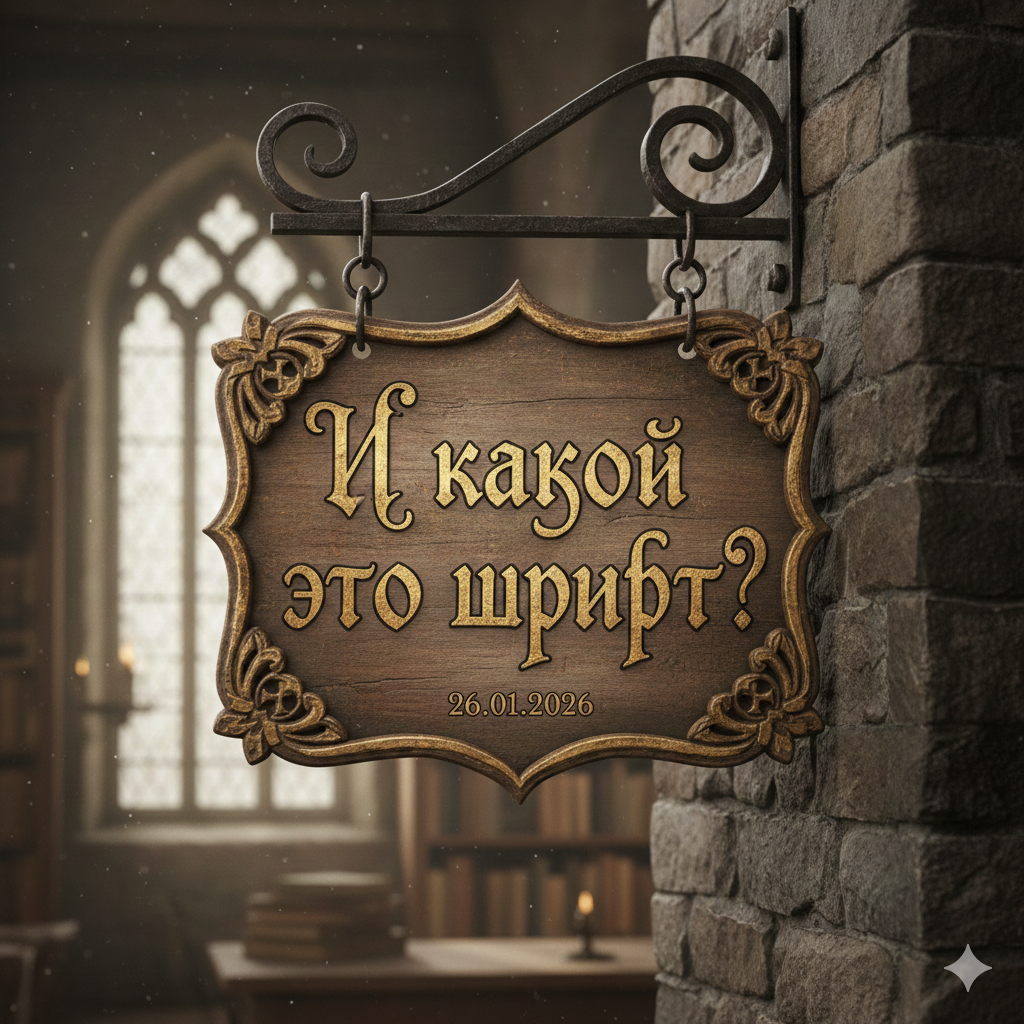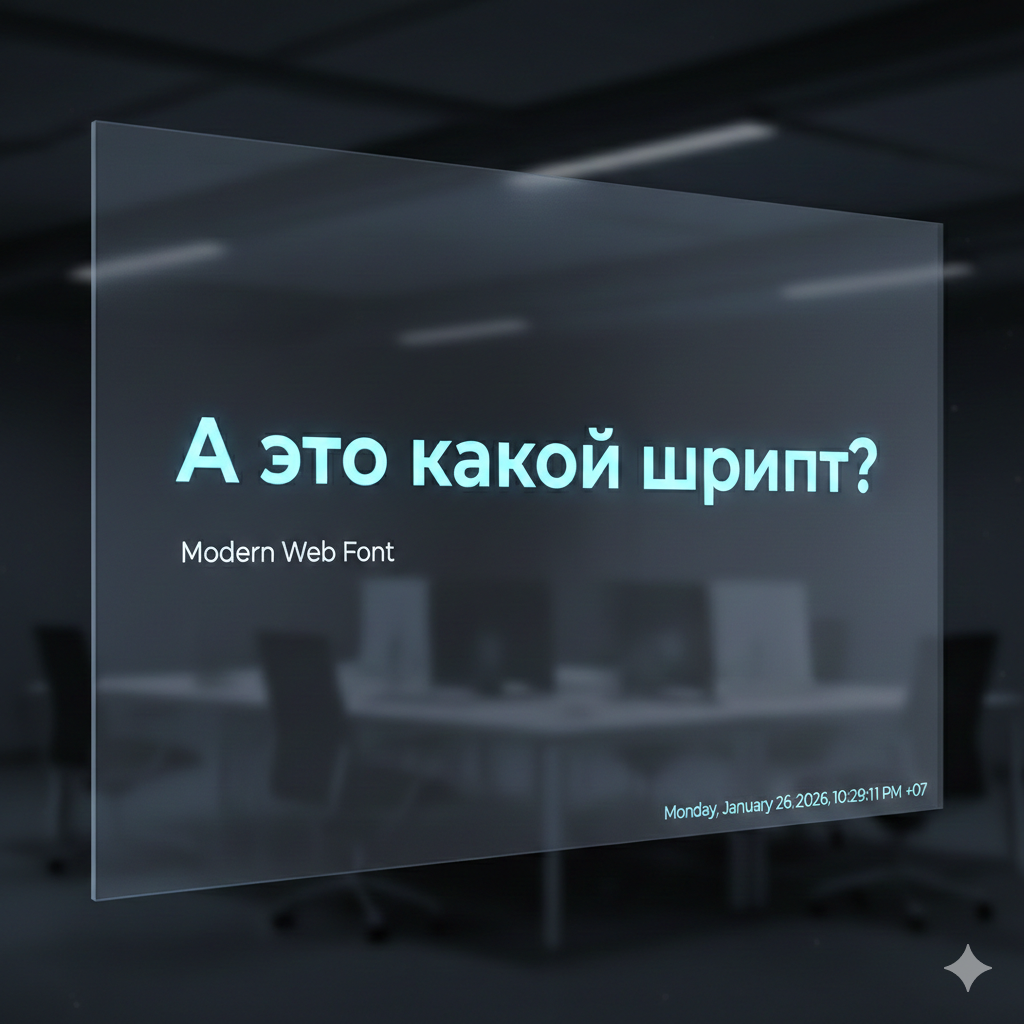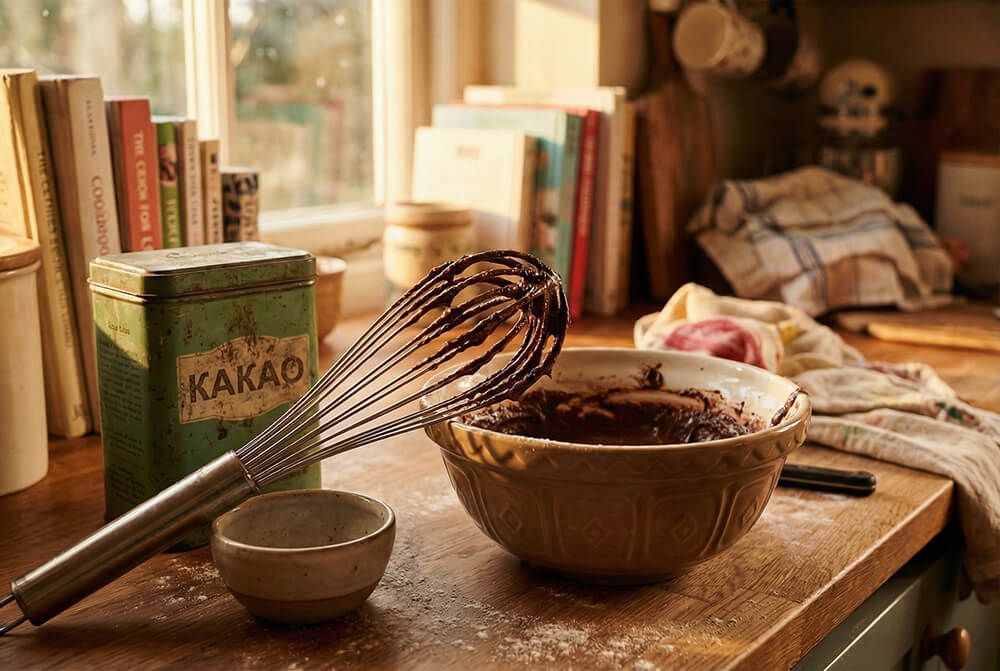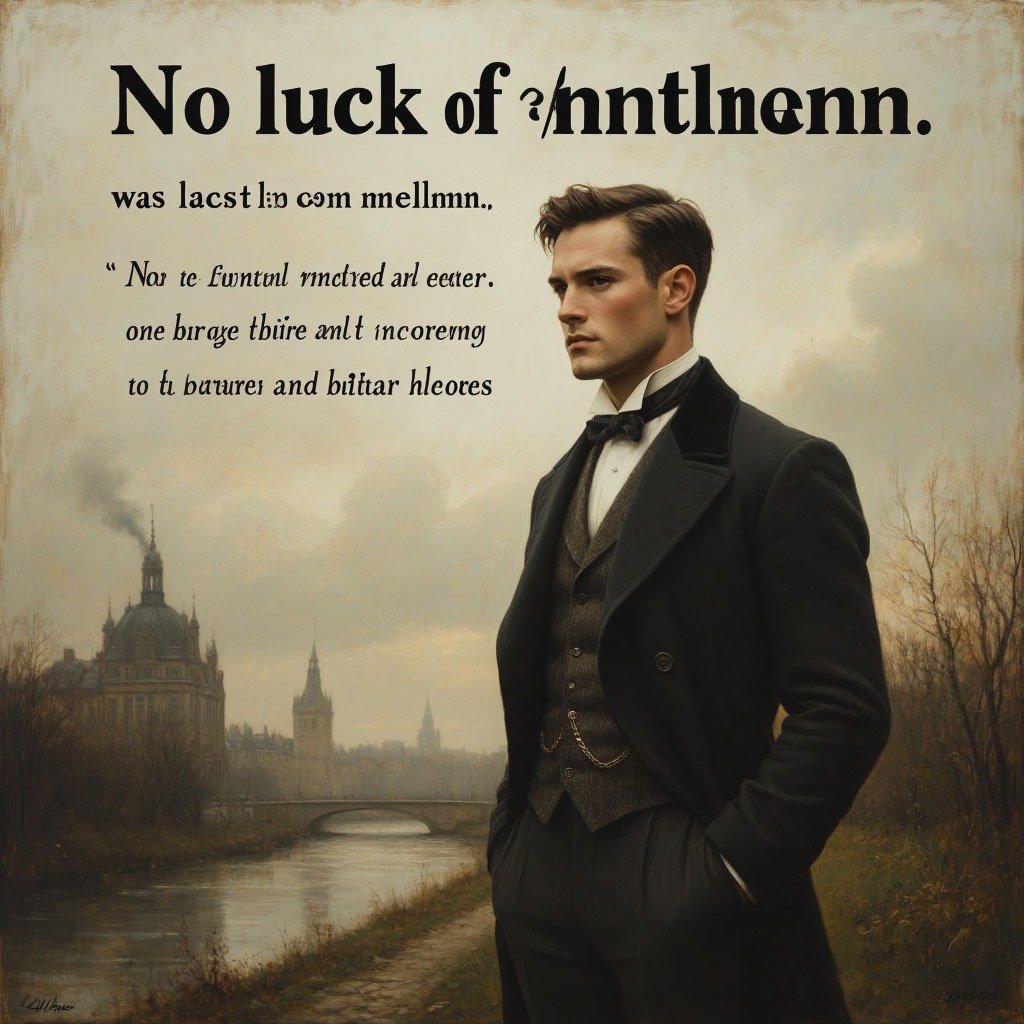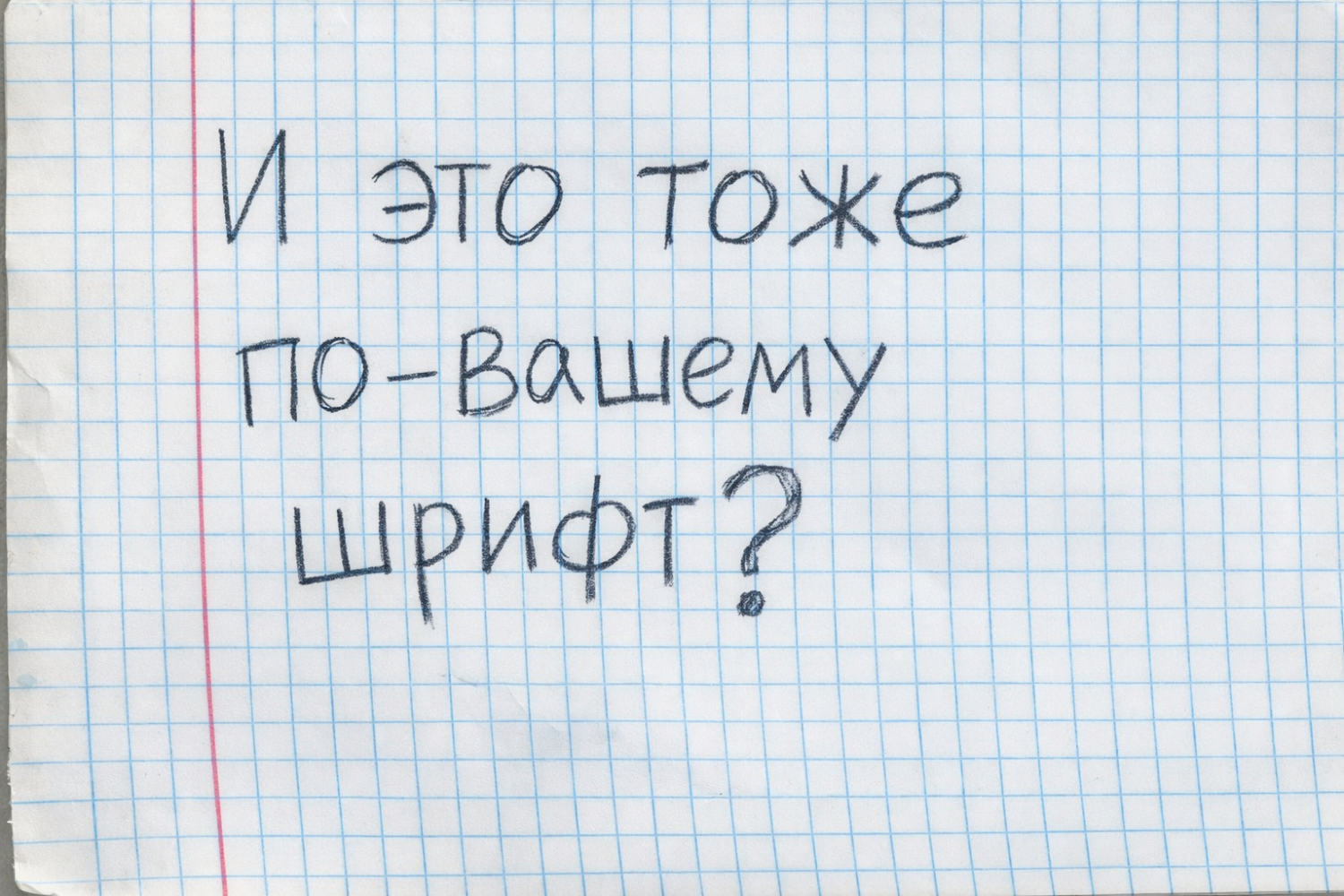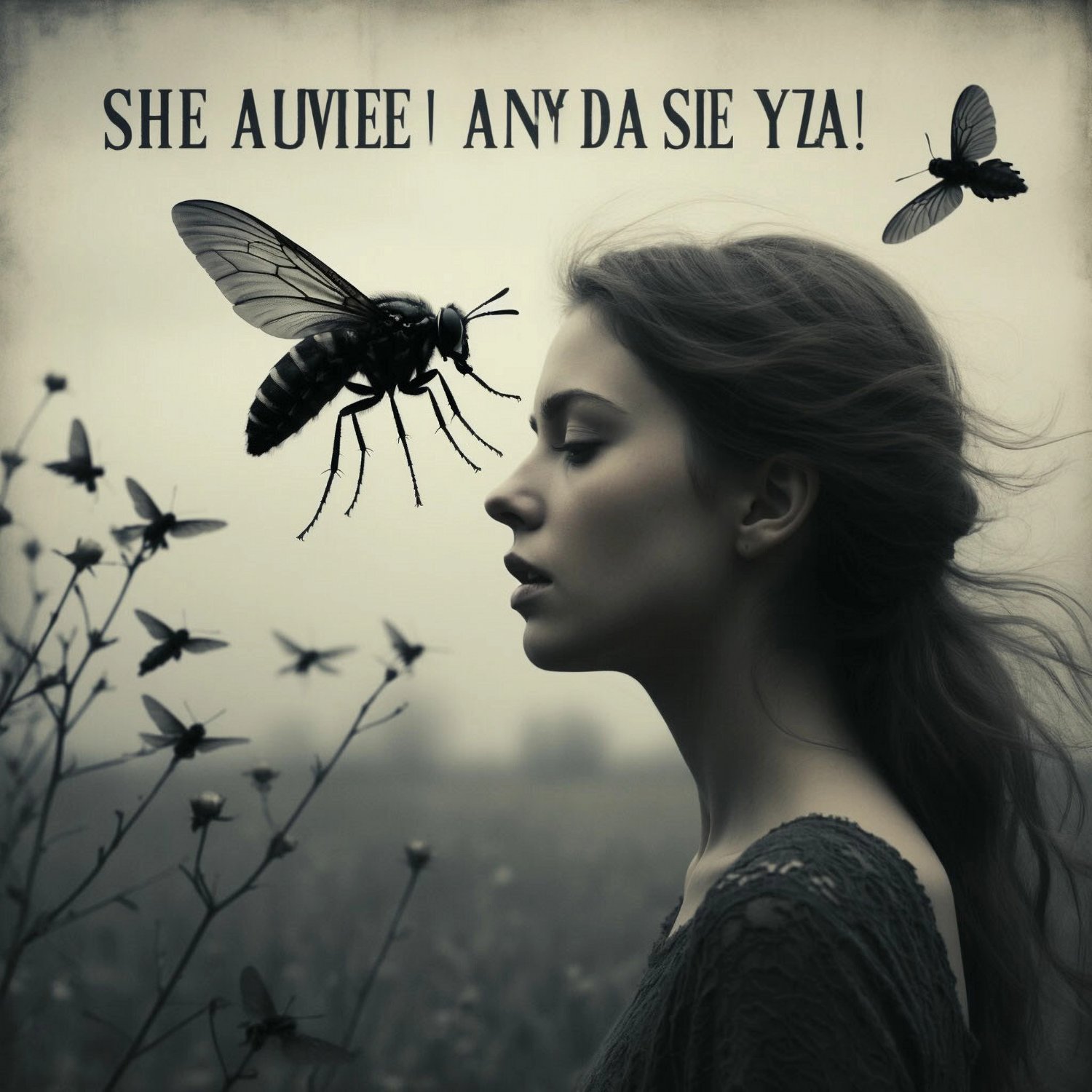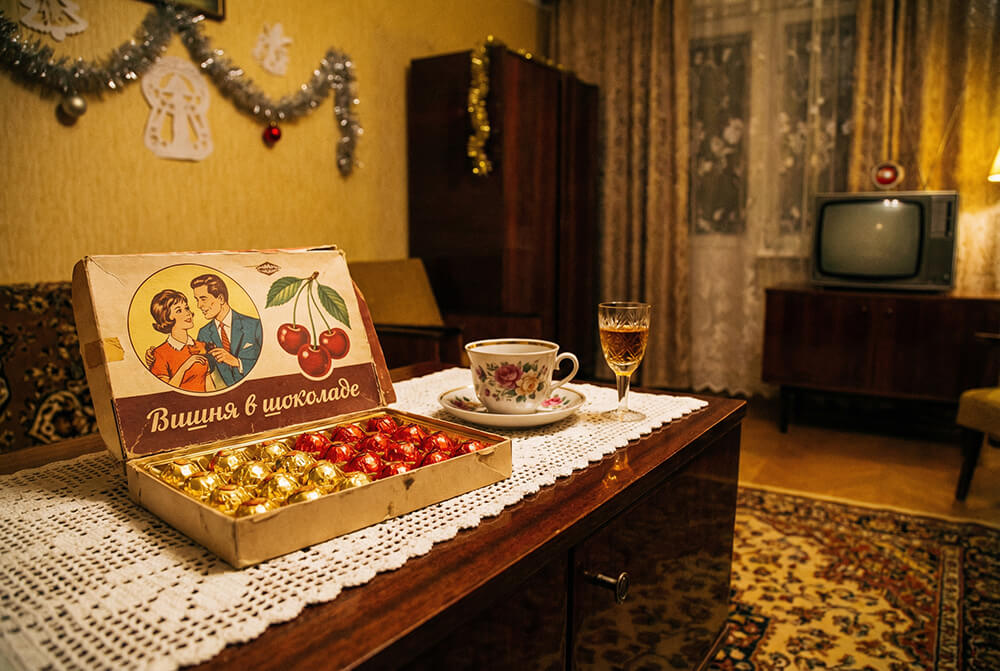
а железяка и шрифты сама придумывает, не берет готовые, как и остальные рефы?Сделано чатом gpt.
Я вот тоже засомневался, но говорят, что да.а железяка и шрифты сама придумывает, не берет готовые, как и остальные рефы?
Даа железяка и шрифты сама придумывает
Прикинь какой ад... "А можно одно слово поменять?"
Берет, но усредняета железяка и шрифты сама придумывает, не берет готовые, как и остальные рефы?
Зачем ей шрифты? ИИ обучаются по картинкам, то есть ему без разницы будет ли это изображение наборов символов шрифтов, картинка серебряной таблички адвокатской конторы или фото памятника на кладбище - лишь бы эти картинки попали в поле зрения ИИ.а железяка и шрифты сама придумывает, не берет готовые, как и остальные рефы?
Затем же, зачем и человек это делает
ахаха ) в ретро-стиль современныешрифты берёт готовые
Ну "Какао" предположим Arial, а "Вишня"?
Смотря что понимать под "готовые" - шрифт с картинки, или лицензированный шрифт, предназначенный для воспроизведения компьютером.шрифты берёт готовые
Не только пишет, но и рисует - типа помеси осы с мухой.Обычно какую то отсебятину пишет
Но другой, тут и то и другое по мотивам.Arctika script
Очень близко
это так слово Fly изобразил (но чаще — бабочек)типа помеси осы с мухой